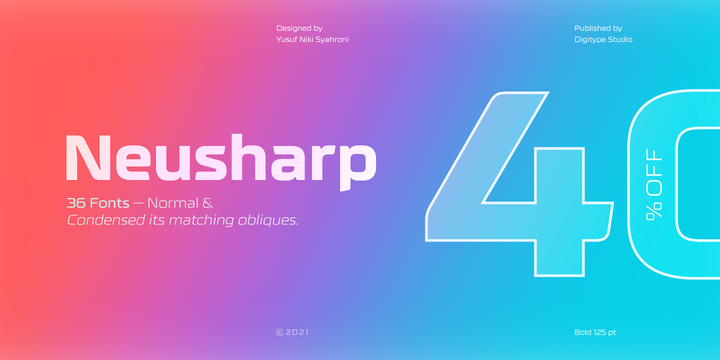
[Myfonts] Neusharp Font (2021)
Шрифт Neusharp отлично подходит для заголовков и коротких абзацев. Он подходит для оформления текстовых цитат, документов, веб-сайтов, логотипов, дизайна на спортивную тематику, журналов и других креативных бизнес-проектов и т.д.
Neusharp - это шрифт без засечек с острыми очертаниями, которые очень впечатляют. Это семейство шрифтов включает в себя 36 шрифтов разного веса и стиля, так что есть множество вариантов, чтобы сделать ваш продукт еще более креативным и привлекательным.